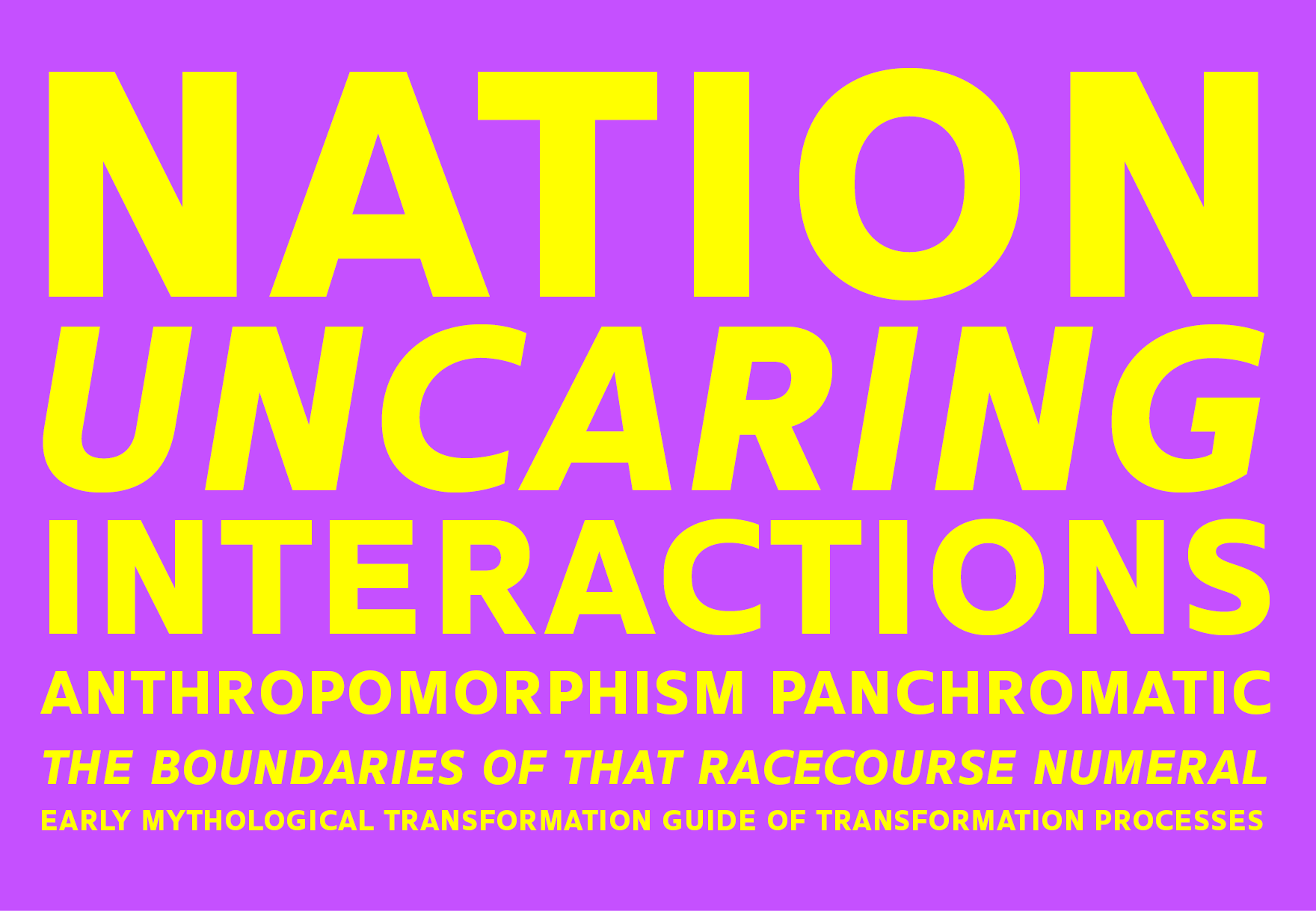
Gemeli
Gemeli,这款字体结构工整、笔画清晰,兼顾美观与易读性,适用于标题、正文、海报、包装、LOGO 等多种场景。字形优雅稳定,风格百搭耐看,适配日常排版与创意设计,让文字呈现更舒适、更具质感。Gemeli一笔一画,皆是细节,以均衡的比例、流畅的线条打造舒适视觉体验,字形端正大气,风格简约现代。无论是商业设计、品牌宣传还是日常排版,都能轻松驾驭,让文字更有格调与力量。Gemeli字体下载。
字体品牌: Production Type 设计师:Jean-Baptiste Levée 字体分类:无衬线体 字体属性:精品字 字符集:Unicode 发布时间: 2018